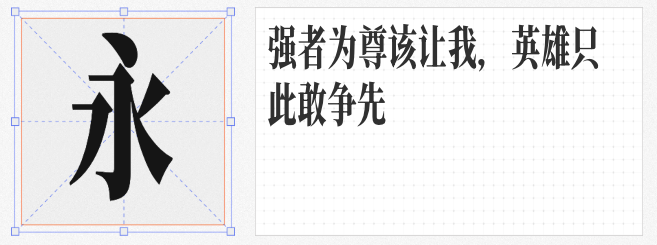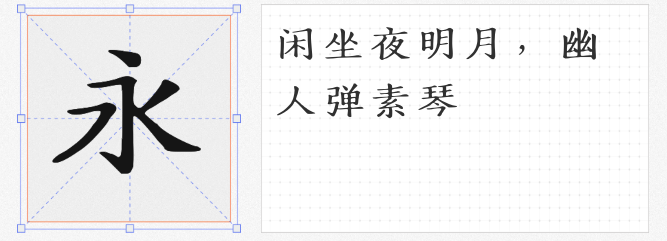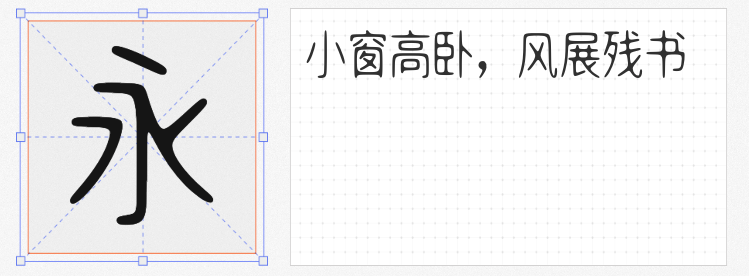
在设计中,字体不仅是信息的载体,更是氛围的营造者。今天为大家精选四款风格清新、氛围感十足的免费商用字体,从短视频标题到长文排版,从品牌设计到广告海报,它们都能轻松驾驭,让你的作品脱颖而出!
由抖音设计博主「猴尊」打造的这款字体,基于思源宋体优化为黄金比例,专为手机竖屏阅读设计。它巧妙拓宽了单行文字容量,让标题更醒目却不显拥挤。重构后的笔画融入书法手写感,既有现代设计的简洁,又保留传统书法的灵动,尤其适合短视频封面、海报大标题,轻松营造高级优雅的视觉氛围。
这款字体以「奏章楷」为灵感,专为长文阅读设计。字形规范中庸,笔画清晰易读,横竖排版皆显端庄大气,仿佛将古代奏章的雅致融入现代设计。无论是书籍内页、合同文档,还是品牌故事长图,它都能以高识别性和书卷气,让文字内容更具说服力,官方场合使用也毫无违和感。
「无锋」二字道尽这款字体的精髓——笔画无折角、无笔锋,整体如水墨凝聚般浑圆流畅。中宫放松、字身修长(高:宽=5:4)的设计,赋予它独特的呼吸感,适合需要营造柔和氛围的场景,如母婴品牌、文艺海报、PPT排版等。极简风格中透着温润气质,让设计更显亲和力。
这款字体个性鲜明,笔画纤细高挑,刚中带柔,既有现代设计的利落感,又不失传统书法的韵律美。无论是品牌LOGO、广告标语,还是电商海报、影视片头,它都能以高挑的姿态和灵活的适配性,成为视觉焦点。刚柔并济的风格,让它成为设计师手中的「万能钥匙」。
这四款字体不仅免费商用,更以独特的风格和实用性,为设计注入清新活力。无论是追求精致感的标题、需要书卷气的长文,还是强调柔和氛围的极简设计,它们都能轻松胜任。赶快收藏使用,让你的作品告别平庸,一秒提升格调!